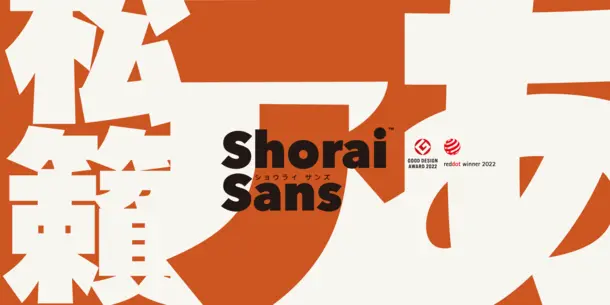
Monotype 日本語書体 Shorai Sans が2022年度グッドデザイン賞に続いて Red Dot Design Award 2022 を受賞
2022年10月28日――米国 Monotype Imaging Inc. の日本法人 Monotype 株式会社(東京都千代田区、以下 Monotype)は、日本語書体 Shorai Sans が2022年度グッドデザイン賞に続いて、世界三大デザイン賞のひとつである Red Dot Design Award 2022 の Brands & Communication Design 部門において、Red Dot Award を受賞したことをお知らせいたします。
■ Shorai Sans の概要
Avenir® Next [*1]の造形的要素を持つ日本語書体「Shorai™️ Sans」は、たづがね®角ゴシック、たづがね角ゴシック Info に続き、約3年の開発期間を経て完成しました。幾何学的でシンプルな美しさと読みやすさが特徴の書体です。付属欧文には和文にあわせてサイズや位置を調整した Avenir Next を採用し、和欧混植に最適化しました。たづがね角ゴシック同様、和文と欧文を別々の書体から選ぶ必要がなく、Shorai Sans 単体で美しく読みやすいテキストを組むことができます。
■ Shorai Sans の特徴
文字の線をできるだけ整理し、骨格を極限まで単純化。線を均一に保つことで、すっきりと読みやすい明快な形を目指しました。シンプルで見やすい文字は、印刷物のほか、スマートフォンやタブレット端末などのデジタルデバイス、建物や標識のサインまで、幅広いニーズに対応しています。
文字の太さは超極太から極細までの10種類。最も太いウェイトの Heavy では、複雑な輪郭線を整理し、Monotype 初の超極太の日本語書体を実現しました。
通常の単体ウェイトに加えて、文字の太さや幅などをユーザー側で自由に調整できるバリアブルフォントを採用し、ウェイト間の太さも調整できます。ウェブサイトや映像などのスクリーン上で動きのある文字表現も可能です。
デザイン開発は Monotype の小林章、土井遼太、そして書体デザインの第一人者、中村征宏氏によって行われました。基本となる漢字400字ができる頃、Monotype の日本、香港、ドイツオフィスの書体デザイナーとエンジニア、そして中村氏が香港に集まり、1週間ほど一緒に書体制作をしました。日本語書体の制作では、書体デザインを終えてからエンジニアにバトンタッチするのではなく、両方を同時に進めた方が効率的であると過去の経験から学んだためです。将来の字種拡張も考慮し、最初から多国籍メンバーで開発を進め、世代や文化を超えたコラボレーションとなりました。人間らしい自然な筆の動きをイメージしたたづがね角ゴシックに対し、Shorai Sans は「何も足さない『素』のかたち」をテーマに、読みやすくクリーンで理知的な印象の書体に仕上げました。
書体名の「Shorai(ショウライ)」は、松の枝を吹き抜ける風やその音の意味である「松籟」に由来しています。茶道では茶釜の湯がたぎる音を意味し、日本的で優雅な響きのある名前です。誰でも発音しやすく、世界中の方々にお使いいただける日本語書体です。
[*1] アドリアン・フルティガー氏と Monotype クリエイティブタイプディレクターの小林章が共同制作した書体ファミリー。オリジナルの Avenir を改刻、ウェイト数を大幅に増やし、OpenType フォントとして2004年に発売。
製品名称 :Shorai Sans(ショウライ・サンズ)
デザイナー :小林章、土井遼太、中村征宏、Monotype Studio